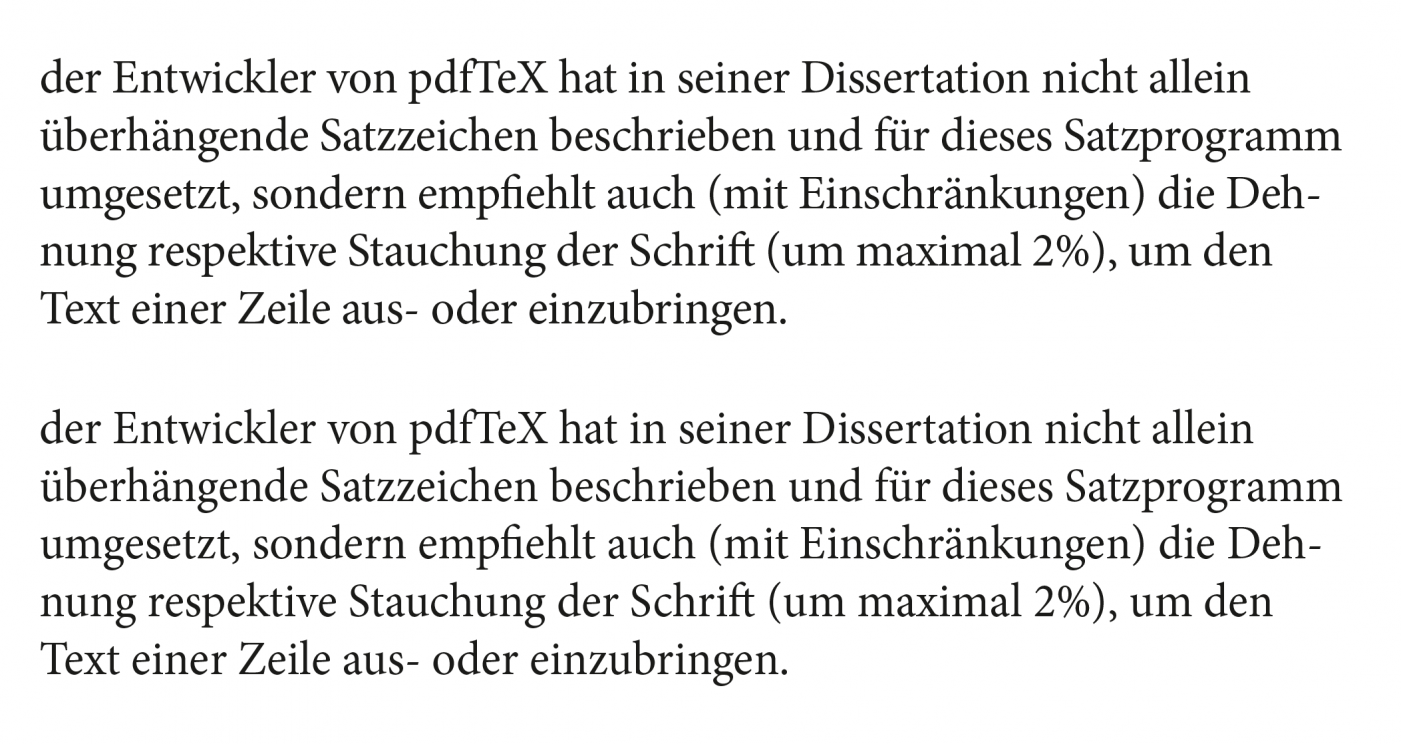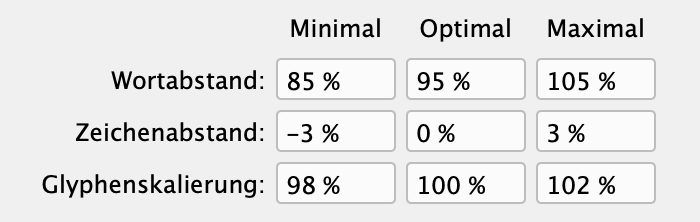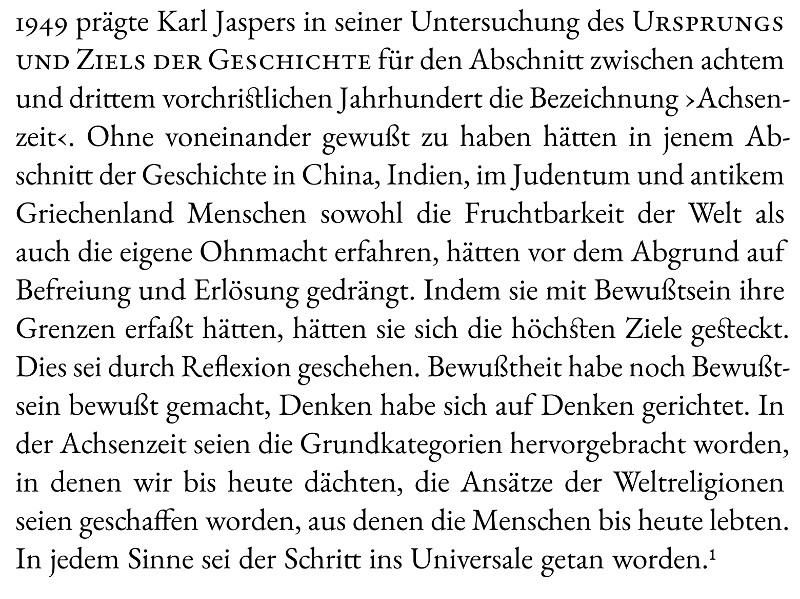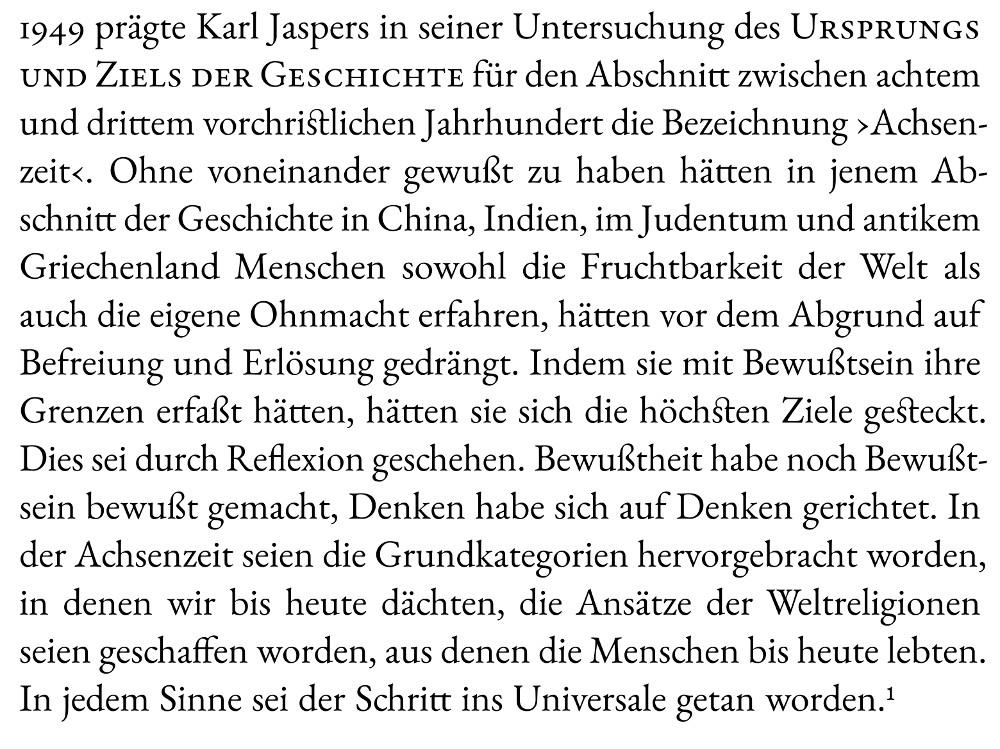
Schriftdehnung im glatten Satz
der Entwickler von pdfTeX hat in seiner Dissertation nicht allein überhängende Satzzeichen beschrieben und für dieses Satzprogramm umgesetzt, sondern empfiehlt auch (mit Einschränkungen) die Dehnung respektive Stauchung der Schrift (um maximal 2%), um den Text einer Zeile aus- oder einzubringen. Da ich keinen Überblick habe, was heutige professionelle Satzprogramme für Möglichkeiten bieten und was üblich ist, möchte ich von Euch gerne wissen, ob eine solche Dehnung bzw. Stauchung mittlerweile als eine zulässige Technik angesehen oder verpönt ist. Und falls es ein zulässiges Mittel ist, sind 2% dann noch die anerkannten Grenzen dafür?
Gedehnt hab ich eine Schrift im Satz noch nie, gestaucht immer wieder mal. Wir machen viel Verpackungen und da muss man Textmengen unterbringen, gesetzliche Mindestschriftgrößen einhalten und so weiter. Eine Stauchung um 2 % sieht niemand, wenn er nicht mit der Nase darauf gestoßen wird, und ist durchaus eine zulässige Technik.
Eine der beiden Texte unten ist in InDesign mit 98 % Breite gesetzt, der andere mit –9 spationiert. Ich könnte dir ohne den direkten Vergleich auf Anhieb nicht sagen, welcher ist.
Ein Kunde von uns nutzt  die PT Serif Pro für längere Texte in Büchern. Da fällt es mir im Blocksatz mit teilweise schon auf wenn zwei aufeinander folgende Zeilen sich sehr von einander unterscheiden. Gefühlt liegt das sehr an der Schrift und einigen schmalen Details wie beim n, p oder a … Generell wären 2 Prozent Skalierung (proportional) für mich aber in den meisten Fällen okay.
Ich werde das so lösen, daß Stauchungen oder Dehnungen über zwei Prozent als problematisch markiert werden. Sowieso wird zunächst der Ausschluß bis zu den eingestellten Grenzen verändert, bevor auf die Dehnung/Stauchung zurückgegriffen wird. Aber so ganz geheuer ist mir dieses Mittel noch nicht. Deswegen werde ich auf jeden Fall eine Möglichkeit einbauen, darauf zu verzichten. In diesem Falle wird dann wieder nur der Ausschluß über die eingestellten Grenzen hinaus gedehnt/gestaucht.
Den Ausschluss stauchen geht streng genommen nicht, er bestünde dann aus Antimaterie ;-) .
Viel wichtiger als die rein zahlenmäßige Formatierung ist doch der optische Eindruck, der erzielt wird. Je nach Schriftart, Buchstabenformen und voreingestelltem Kerning kann ein auf 98 % gestauchter Buchstabe, Wort, Absatz besser aussehen als eine negative Spationierung, aber das muss eben im Einzelfall untersucht werden. Eine grundsätzliche Aussage, dass dieses oder jenes typografische Mittel besser oder schlechter wäre, gibt es nicht – das Ergebnis muss passen.
Da stimme ich Dir durchaus zu. Deswegen versuche ich auch so viel als möglich manuell und nicht automatisch ablaufen zu lassen. An der Stelle sollte ich vielleicht erwähnen, daß ich mit einem eigenen Satzsystem arbeite, bei dem ich nun eine neue Version programmiere, in der ich eben auch die Dehnung der Schrift beim glatten Satz als eine Möglichkeit bieten will, Zeilen ein- oder auszubringen.
Da es sich um virtuellen Ausschluß handelt, darf der auch gerne als virtueller Antimaterie bestehen. 😉 Bisher hat der Umgang damit jedenfalls hervorragend funktioniert, auch über längere Strecken. So habe ich mit meiner Software (allerdings schon der vorletzten Version) Benjamins Aufsatz Das Kunstwerk im Zeitalter seiner technischen Reproduzierbarkeit umgesetzt, was immerhin Material im Umfang von beinahe Spielfilmlänge ergibt (ich arbeite mit kinetischer Typographie).
Bisher habe ich versucht, mich möglichst nicht nur von dem unmittelbaren ästhetischen Eindruck leiten zu lassen, der fraglos letztlich entscheidend sein muß, sondern von der seit Jahrhunderten geübten Typographischen Praxis zu profitieren. Daß Satzregeln immer nur Leitplanken sein können, über die man sich im Einzelfall auch mal hinwegsetzen muß, ist mit durchaus klar. 🙂
Die "seit Jahrhunderten geübte typographische Praxis" gibt es nicht. Je nach Entwicklungsstand war und ist die Praxis immer unterschiedlich. Dehnungen und Stauchungen beispielsweise gingen im Bleisatz noch nie, wie auch, hätte man doch angepasste Lettern benötigt.
An der Stelle muß ich Dir aber dann doch widersprechen: Typographische Praxis gibt es mindestens, solange es den Satz mit beweglichen Lettern gibt, was allerdings nicht heißt, daß sie immer einheitlich war.
Aber was soll das, hier Spitzfindigkeiten auszutauschen?
Ich bin dann mal weg und bedanke mich noch mal für die Auskünfte. 🙂
vor 18 Minuten schrieb prolysarik:
Aber was soll das, hier Spitzfindigkeiten auszutauschen?
Das ist keine Spitzfindigkeit – mir hat sich noch nicht erschlossen, was du mit "seit Jahrhunderten geübte typographische Praxis" meinst. In meinen Augen gibt es diese nicht.
Ich versuche es mal ganz ironiefrei zu erklären (auch wenn es schwer fällt):
Praxis: von altgriechisch für 'Tat', 'Handlung', 'Verrichtung'.
Gutenberg erfand im 15. Jahrhundert den Buchdruck mit beweglichen Lettern (und damit den Satz)
Vielleicht wäre ja ein Mix aus allen Möglichkeiten der beste Weg:  die Hälfte dessen, was da gestaucht oder gestreckt werden muss durch Änderung des Buchstabenabstands korrigieren, damit die Zeile nicht zu lückenhaft oder zu dunkel wird, und dann den verbleibenden Teil durch strecken oder stauchen der Glyphen selbst, damit die nicht sichtbar ihre Geometrie ändern müssen. Vielleicht zusätzlich, wird gestreckt wahlfreie Ligaturen, wie ch, ck dann auflösen.